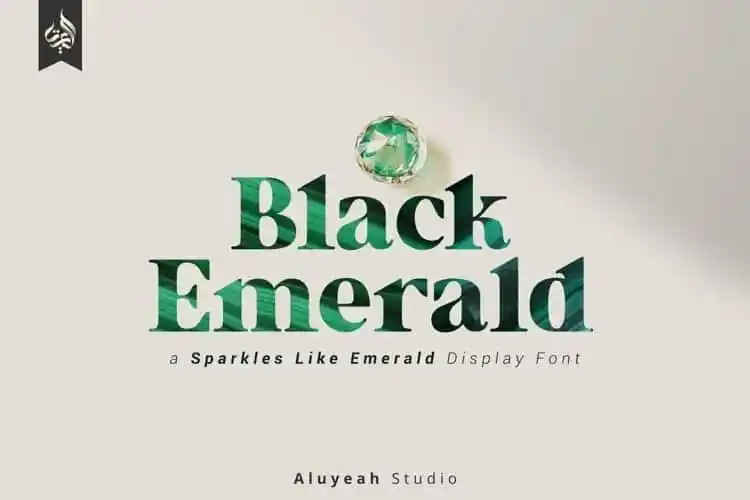
A Black Emerald Serif Font oferece uma experiência visual envolvente e natural para designers gráficos atentos à sofisticação. Com contraste alto e forma única dos caracteres, essa serif transmite elegância e beleza de um modo que vai além das formas tradicionais. A fonte inclui estilos regulares e sobrescritas para complementar qualquer design, destacando-se como um elemento chamejante de esmeralda que transforma projetos em designs perfeitamente fashionáveis, belos, sofisticados e elegantes. Para quem busca expressar a melhor versão de si mesmo através da tipografia, Black Emerald Serif é uma escolha irresistível.